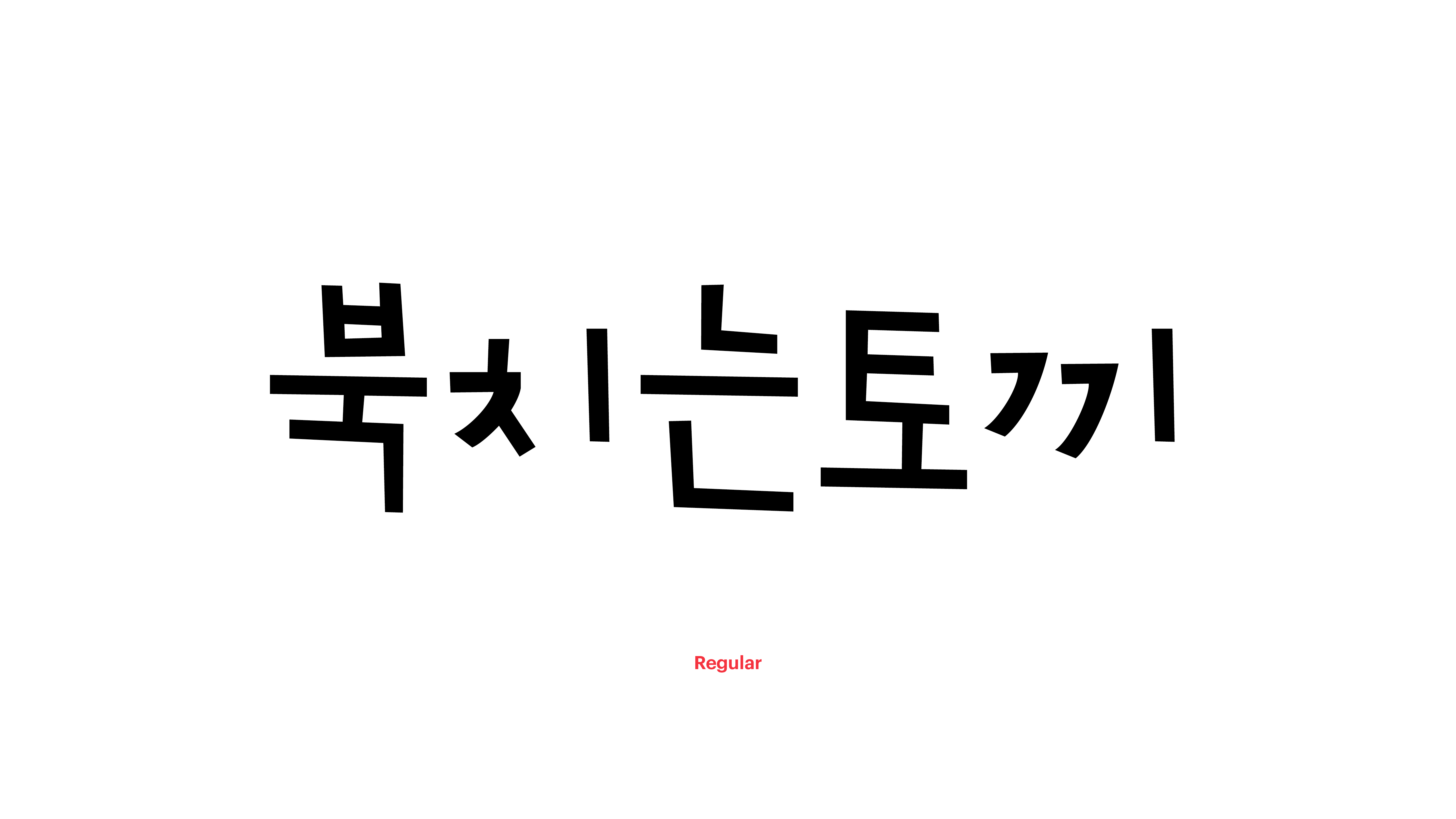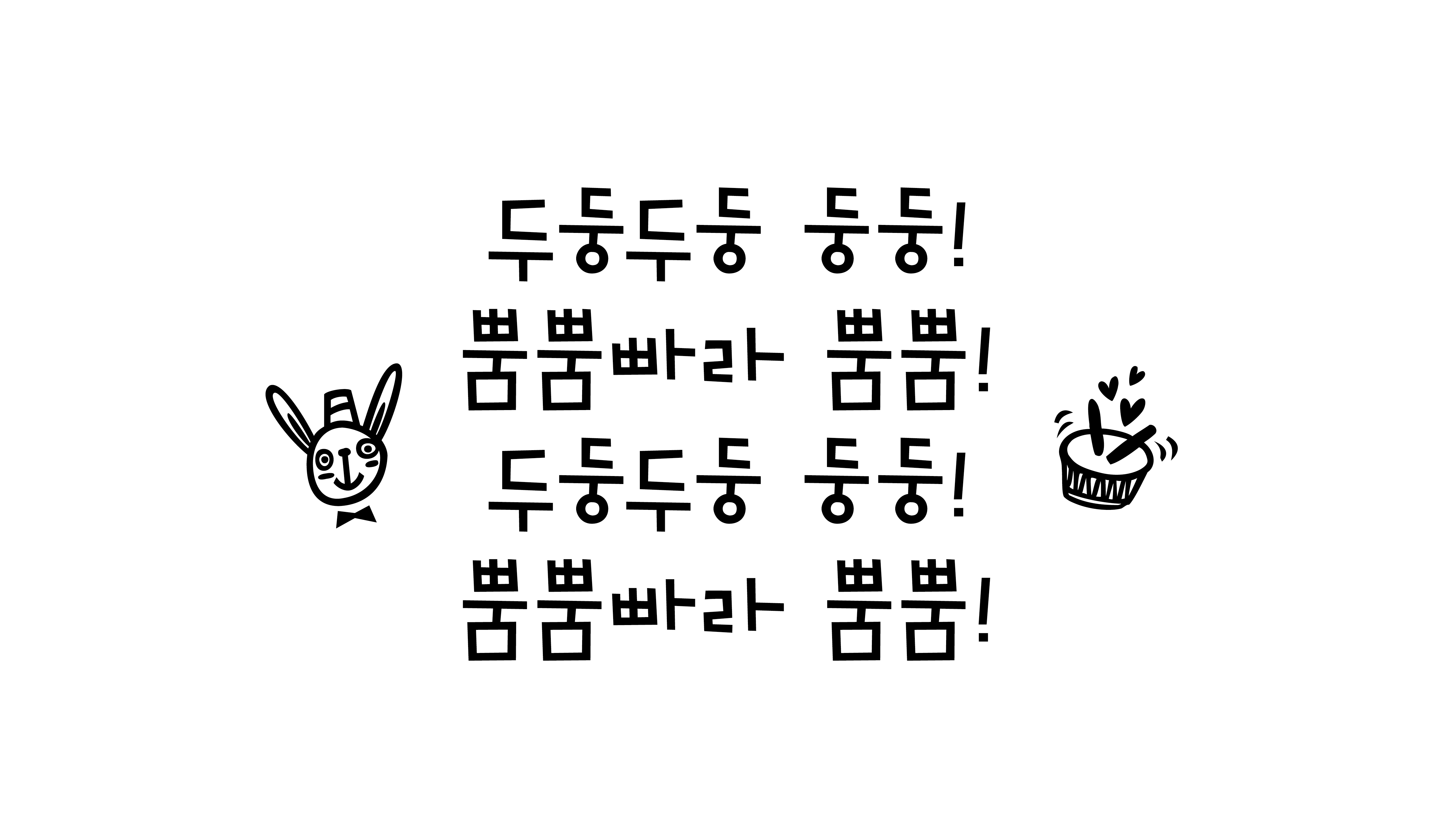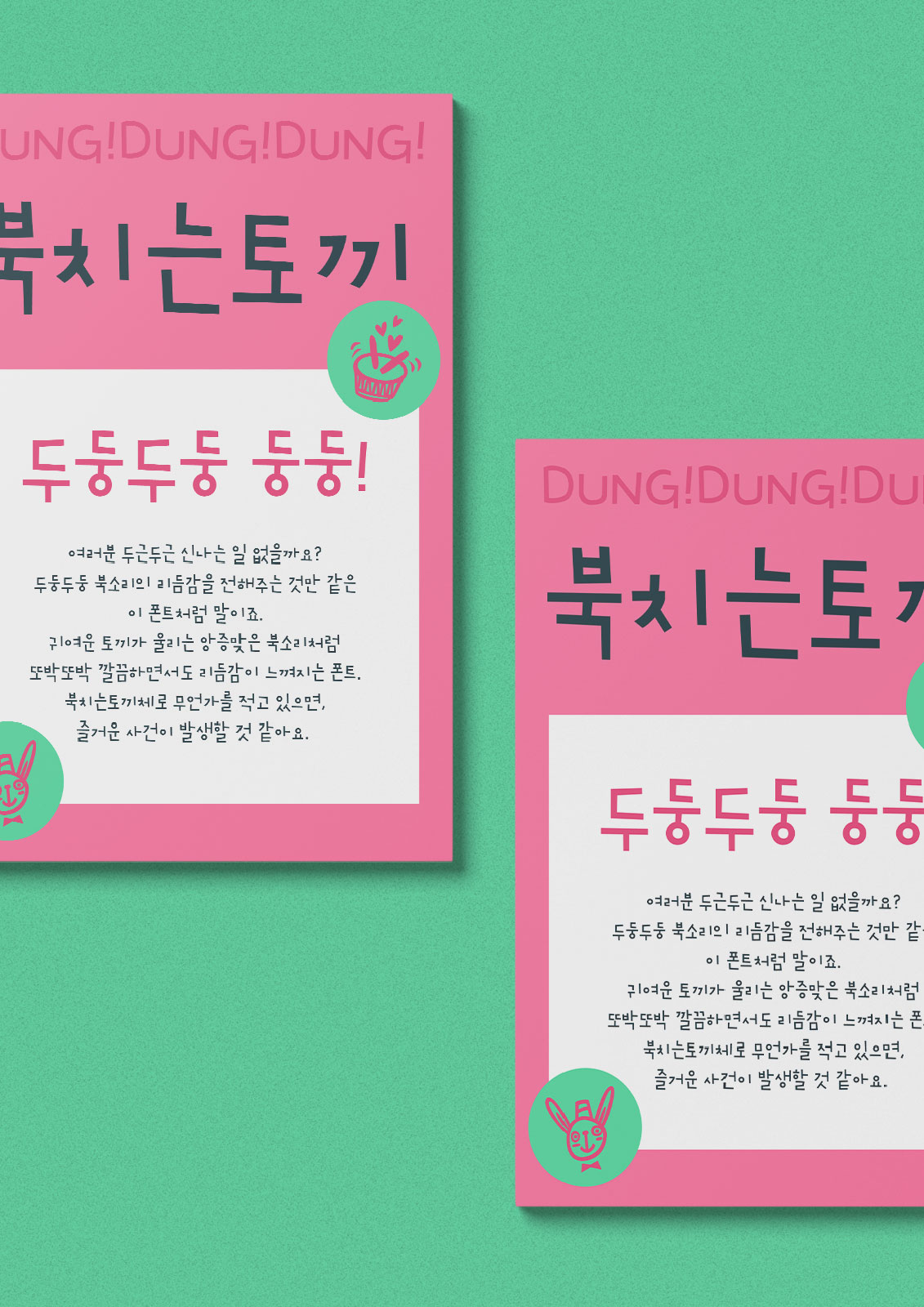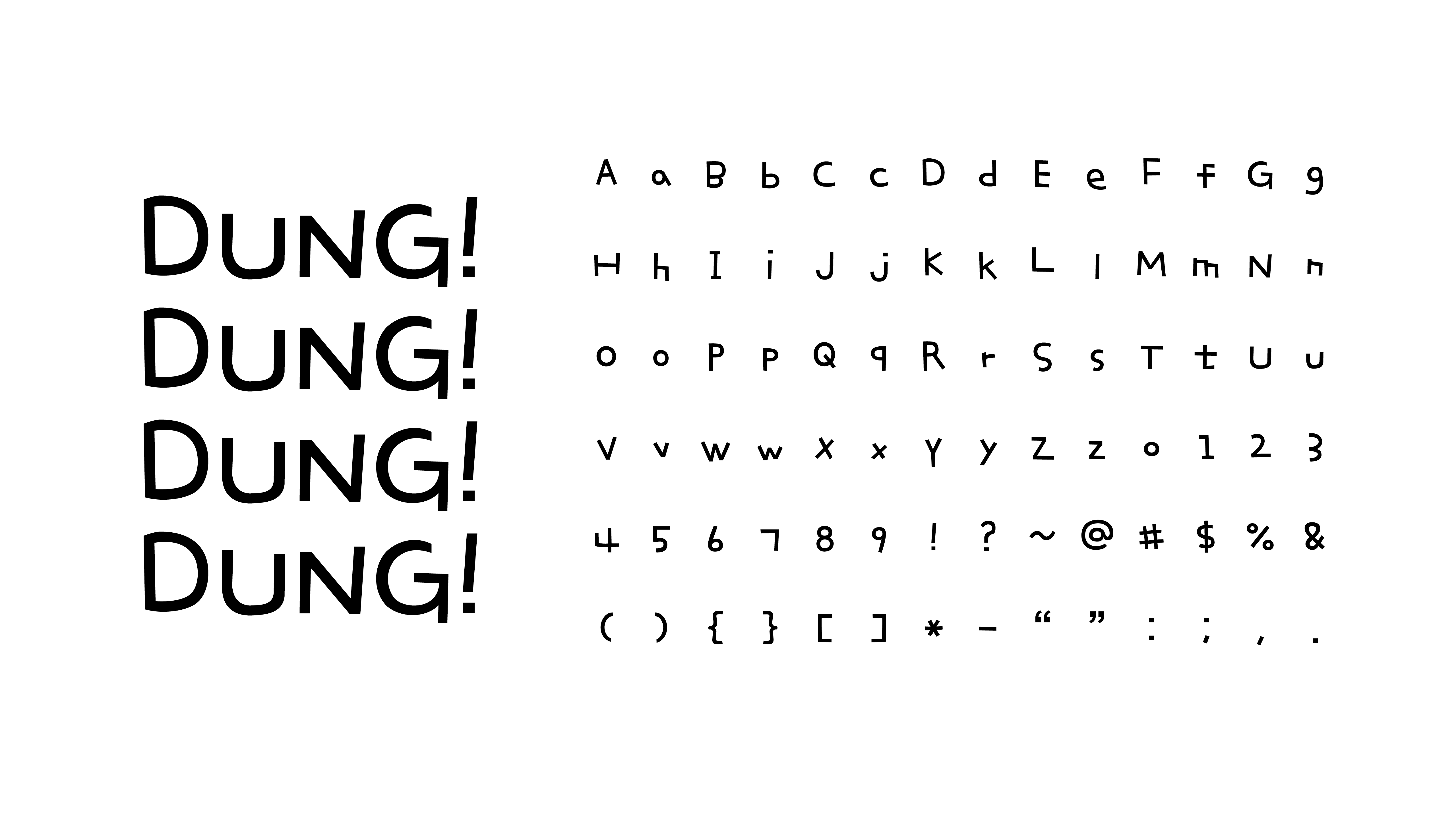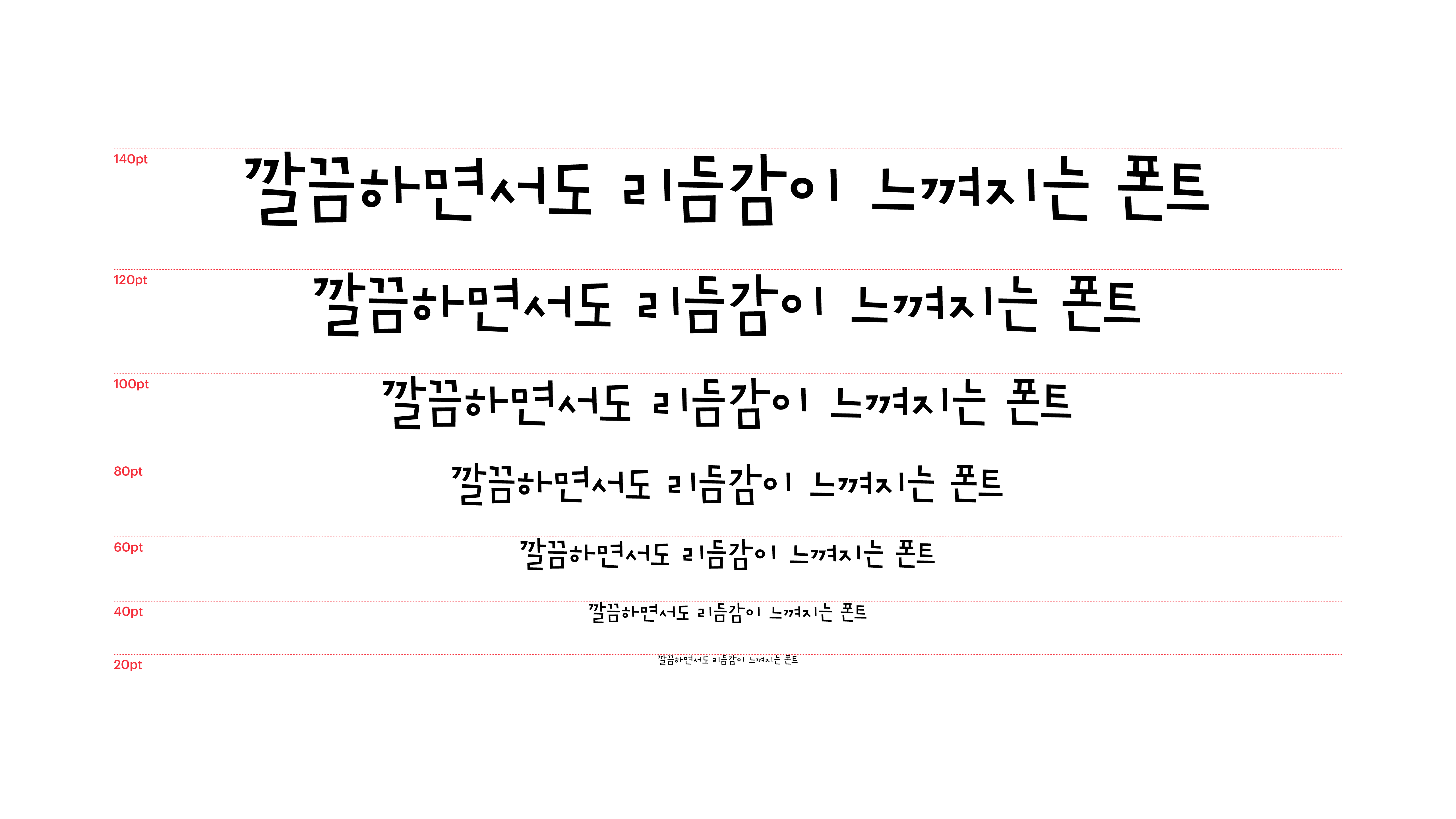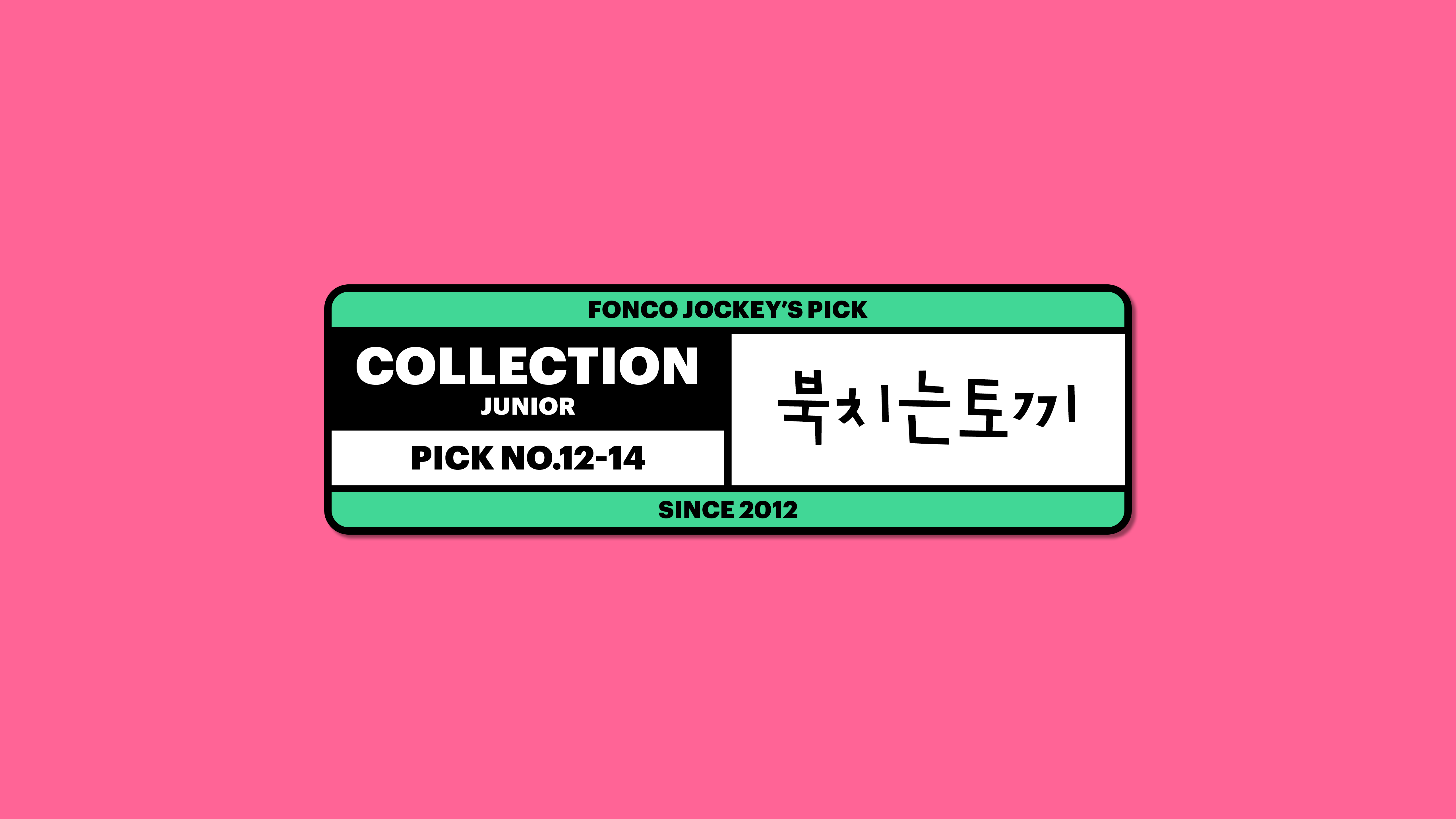
북치는토끼
Yoon 북치는토끼
여러분 두근두근 신나는 일 없을까요? 두둥두둥 북소리의 리듬감을 전해주는 것만 같은 이 폰트처럼 말이죠. 귀여운 토끼가 울리는 앙증맞은 북소리처럼 또박또박 깔끔하면서도 리듬감이 느껴지는 폰트. 북치는토끼체로 무언가를 적고 있으면, 즐거운 사건이 발생할 것 같아요.